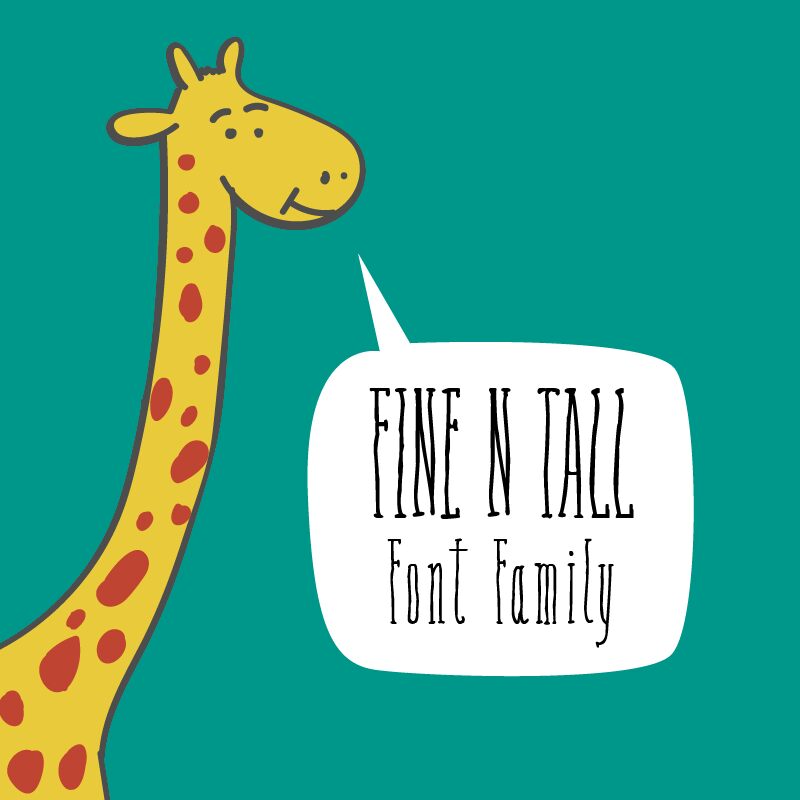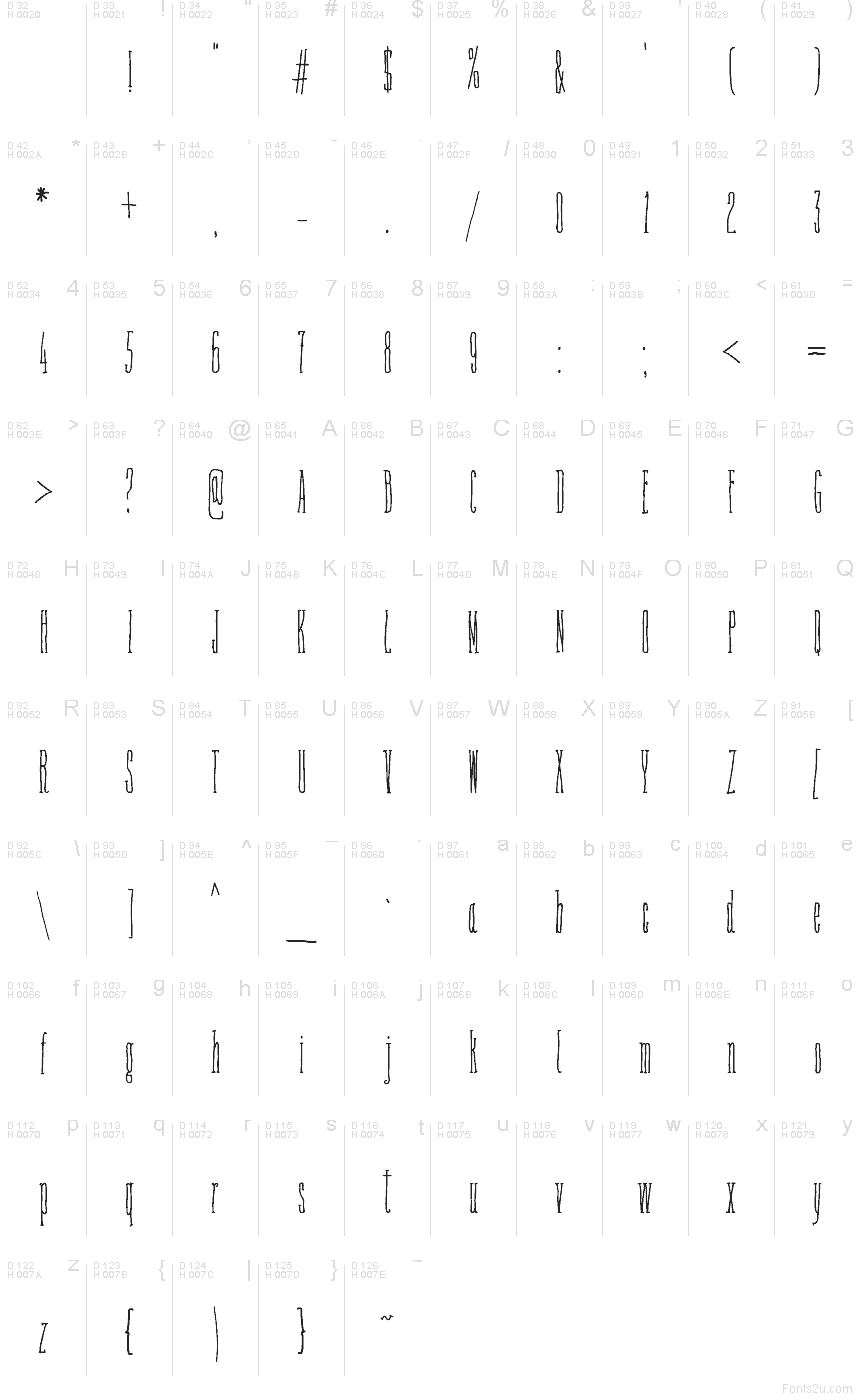
Fine N Tall autorstwa Galdino Otten Fonts to darmowy odręczny krój pisma typu display o niezwykle smukłych literach i klimacie staromodnej książki z bajkami. Jego nieregularne pociągnięcia i drobne, zakręcone detale nadają formom żywotność.
Okładki książek są dla niego najbardziej naturalnym środowiskiem, ponieważ górujące kształty mogą sprawić, że tytuł wygląda tak, jakby został wyjęty bezpośrednio z osobliwej opowieści. Nadaje się również do opakowań butikowych, plakatów teatralnych oraz zaproszeń o kapryśnym lub lekko upiornym motywie. Obok rysunków piórkiem i tuszem lub delikatnych rycin botanicznych cienkie liternictwo może stać się częścią ilustracji, zamiast być osobną etykietą.